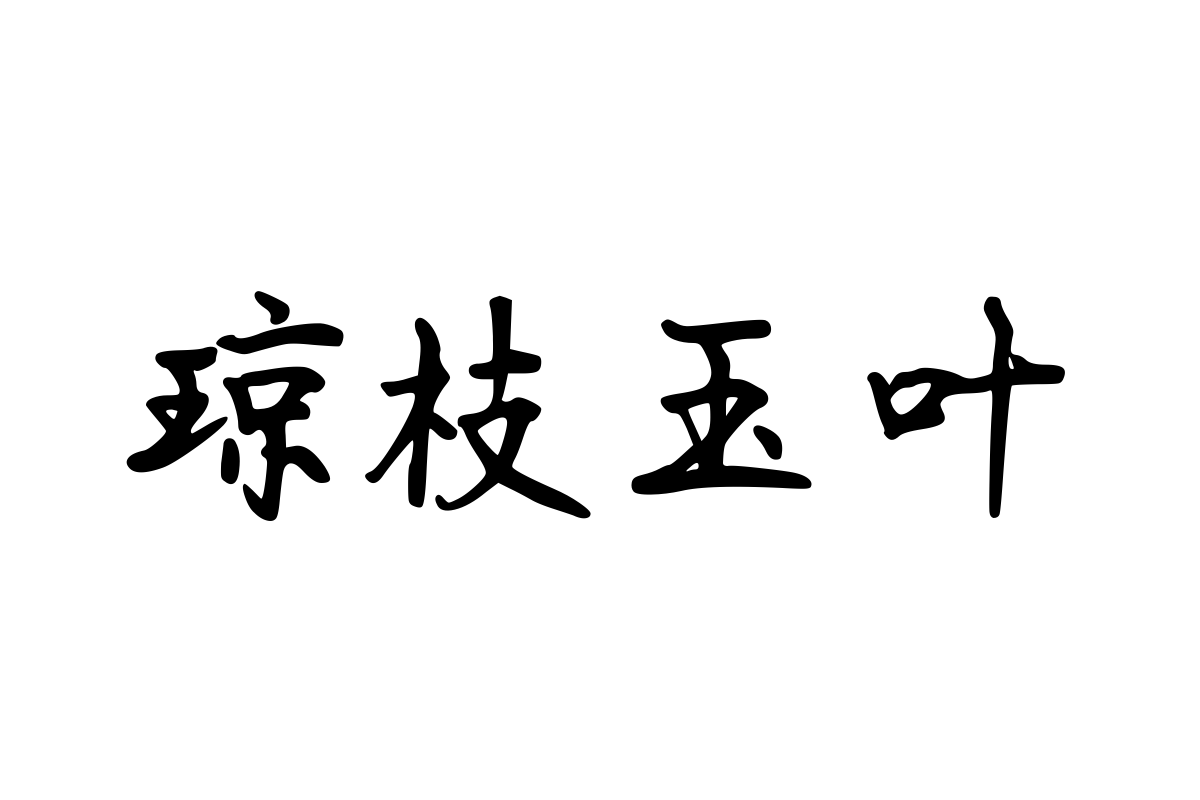
思雨鹧鸪飞是一款具有独特风格的中文字体,它采用了现代的设计手法,将传统书法元素与现代设计相结合。这款字体的特点在于其流畅的笔画和独特的字形结构,给人一种优雅而有力的感觉。
思雨鹧鸪飞的字体大小为16号到24号,适用于各种应用场景,如标题、正文、广告等。它的笔画粗细适中,既有力度又不失柔美,适合用于需要表现力量感的场合。此外,这款字体还具有较强的可读性,即使在较小的字号下也能保证清晰易读。
思雨鹧鸪飞的设计风格独特,线条流畅,字形饱满,具有很强的视觉冲击力。它的使用可以提升文字的整体美感,使文本更加生动有趣。同时,这款字体也具有较高的辨识度,易于识别和记忆。
总的来说,思雨鹧鸪飞是一款具有现代感和传统韵味的中文字体,适合用于需要表现力量感和独特风格的场景。